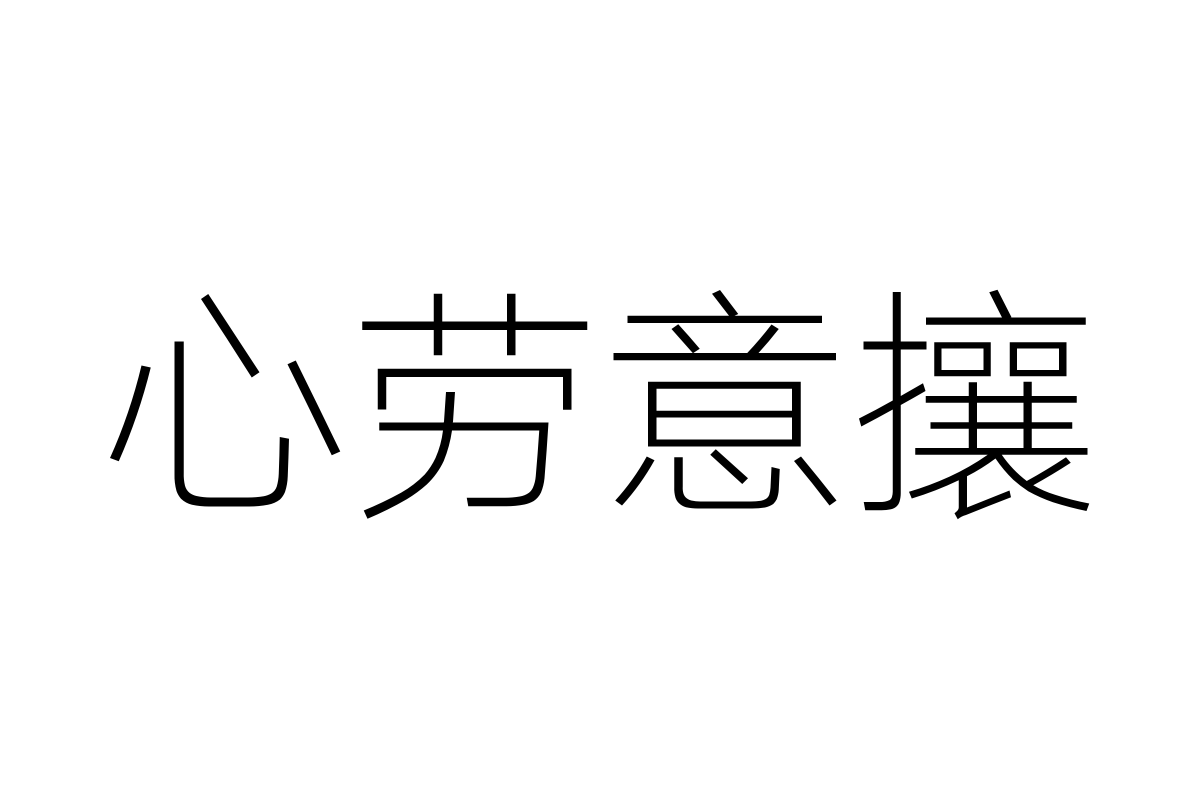
汉仪旗黑-35是一款具有现代感的中文字体,适用于各种商业和设计项目。这款字体的特点是笔画流畅,结构紧凑,给人一种简洁明了的感觉。它的线条粗细适中,既有力量感又不失柔和,非常适合用于标题、广告、标志等需要突出品牌或产品特点的设计场景。此外,汉仪旗黑-35还具有一定的可读性,适合用于正式的商业文件和出版物。